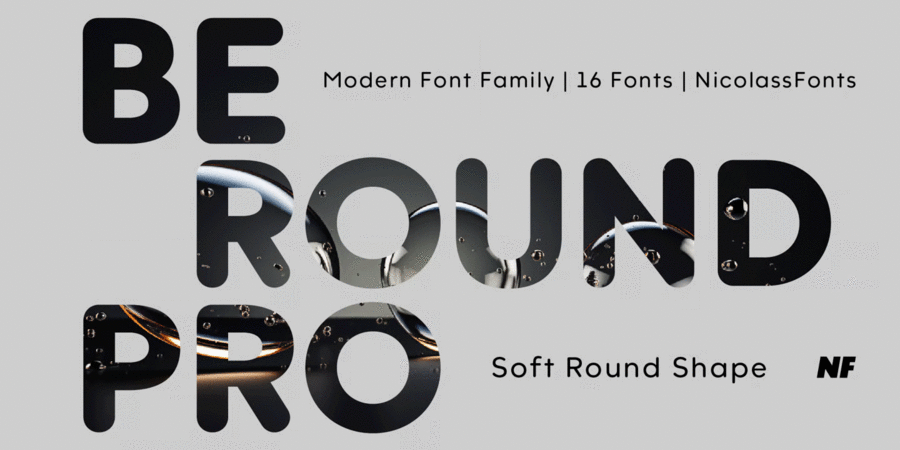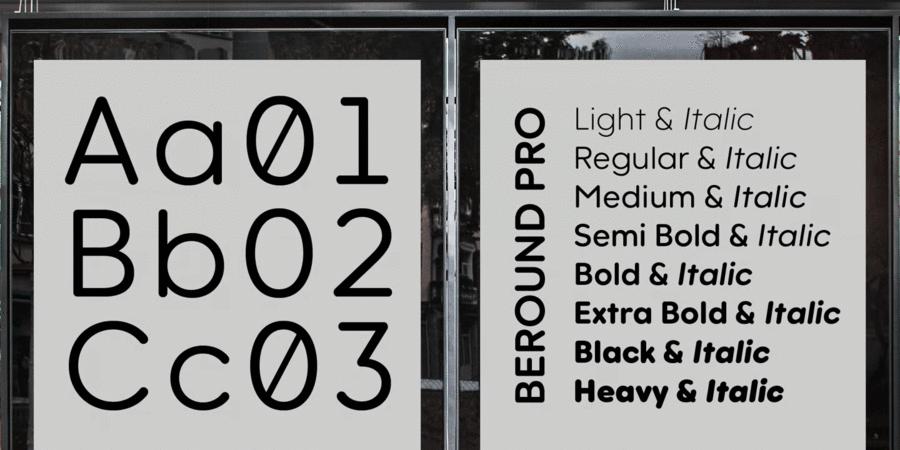
Опис гарнітури Beround Pro — це сучасна багатомовна гарнітура, заснована на шрифтовому сімействі Beround, що відрізняється м'якими, заокругленими формами. Вона включає 16 накреслень: 8 прямих і відповідні їм курсиви. Кожен шрифт містить 1000 гліфів і підтримує функції OpenType, що робить його універсальним вибором для брендингу, маркетингу та цифрового дизайну. Шрифт розробив Микола Савчук у 2024 році.
Асоціації з сімейством шрифтів Beround ProОсобистість і характер гарнітури:
делікатний, чистий, легкий, прохолодний, свіжий, модний, тонкий, сучасний, лаконічний, ясний, рівний, смачний, якісний, прозорий, інтимний, ніжний, повітряний, дротяний, статичний, комфортний, затишний, гладенький, домашній, зрозумілий, спокійний, М'який, приємний, неоновий, мирний, симпатичний, милий, яскравий, Простий, примітивний, зручний, добрий, привітний, доброзичливий, пластмасовий, дитячий, щедрий, пишний, сімейний, рясний, насичений, наївний, грайливий, мультяшний, святковий, важкий, масивний, товстий, пухкий, сильний, апетитний, помітний, активний, гумовий
лосьйон, краса, туалетна вода, шампунь, косметика, мода, дієта, латте, АСМР, Інстаграм, ранок, ліки, здоров'я, мафін, смузі, одяг, взуття, інтер'єр, спальня, дім, вода, небо, їжа, Місто, іграшка, дитяча книжка, шоу, телебачення, чай, Хюґе, родина, молоко, дитяче харчування, булочки, булочка, десерт, торгівля, сир, кондитерська, солодощі, випічка, булочна, кафе, гра, м'яка іграшка, кава, соус, сметана, кетчуп, підгузок, селфі, малюк, кухня, розфарбування, жуйка, чіпси, подушка, анімація, мультфільм, подарунки, свято, дитячий ранок, дитсадок, сік Гарнітура асоціюється з віком: